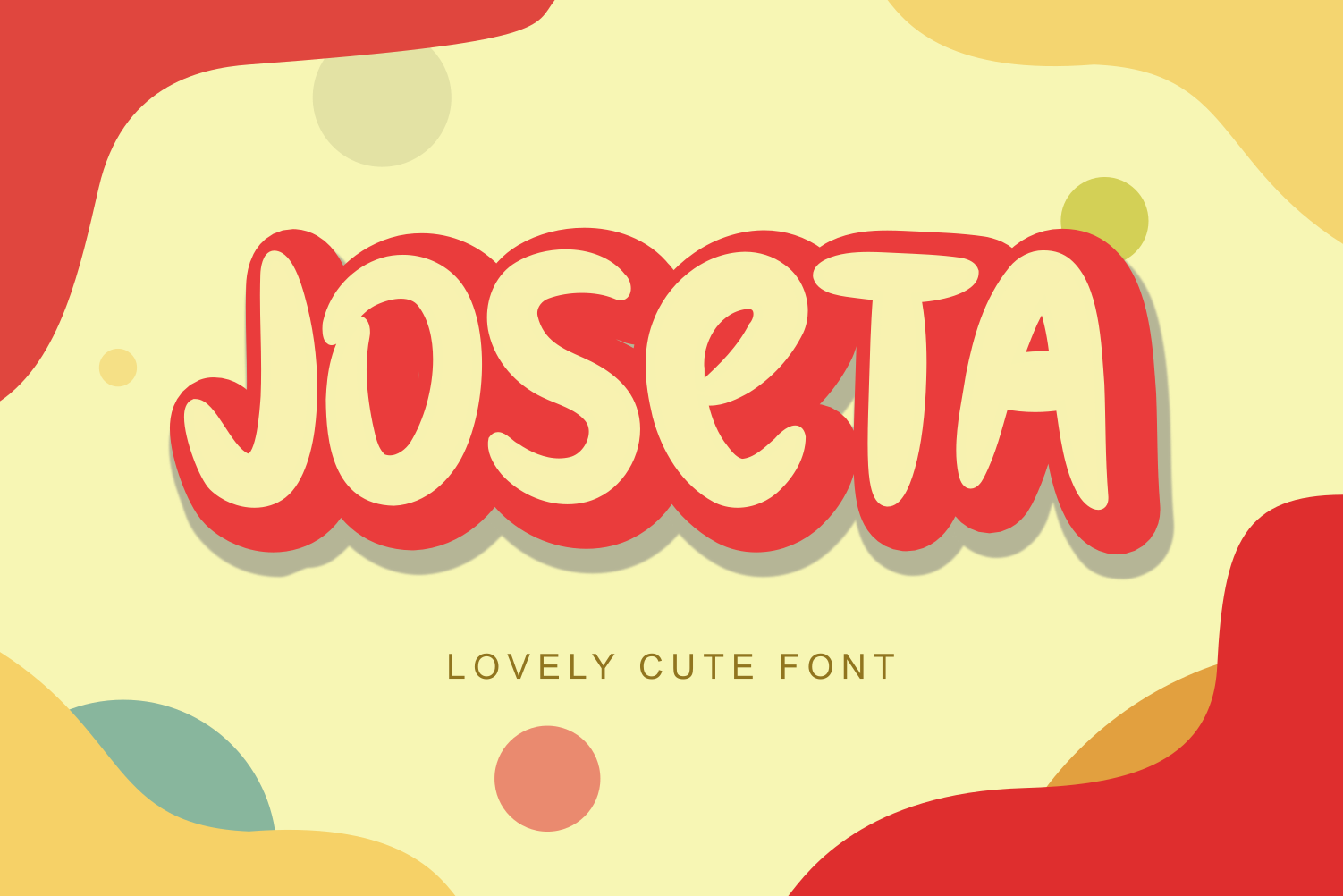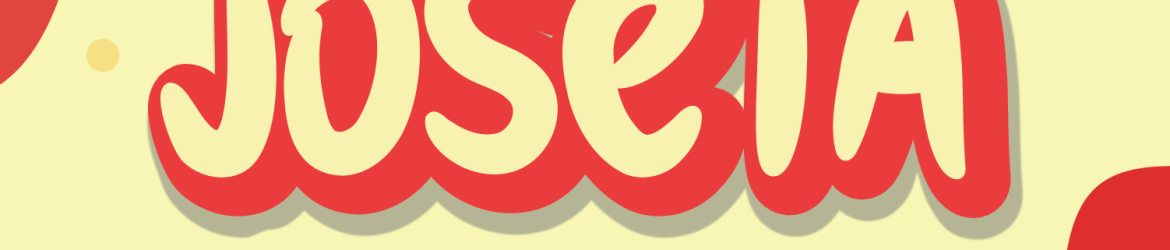
A fonte Joseta é perfeitamente adequada para aplicar uma pitada de leveza a qualquer projeto visual, seja ele na forma de cartões de aniversário encantadores ou t-shirts criativas dos seus filhos. Suavemente sugestiva e cheia de vida, esta fonte robusta se destaca tanto no estilo elegante quanto nos temas mais coloridos, como projetos para crianças, capas de livros e até mesmo cartões de felicitações personalizados. A Joseta também é um escolher ótimo para quem procura algo que brinque ao mesmo tempo em sua simplicidade, sendo ideal para qualquer aplicação onde você deseja adicionar uma cor a mais à sua identidade visual. Seja o seu próximo projeto de design com cartões personalizados, capas de livros ou até mesmo as estampas de t-shirts dos seus filhos, Joseta certamente ajudará a garantir que suas criações se destacem, sempre com um toque delicado e divertido.